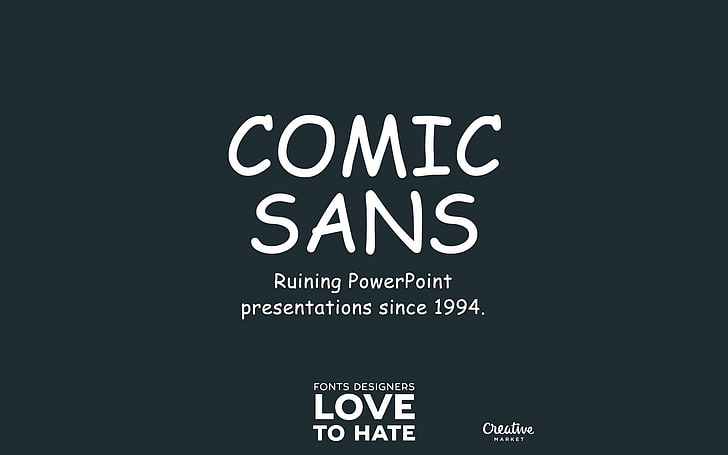
Font VNF Comic Sans
Font chữ VNF Comic Sans là một phiên bản Việt hóa của phông chữ Comic Sans nổi tiếng, mang lại cảm giác thân thiện, vui tươi và dễ gần. Với các đường nét mềm mại, không góc cạnh, phông chữ này thường được sử dụng trong các thiết kế không chính thức, mang tính chất giải trí, giáo dục hoặc các tài liệu hướng đến trẻ em. VNF Comic Sans thuộc bộ sưu tập Font Chữ VNF phù hợp để tạo ra các ấn phẩm như thiệp mời, poster, bảng thông báo hay nội dung số cần sự nhẹ nhàng và thoải mái, giúp truyền tải thông điệp một cách thân thiện và dễ tiếp cận.